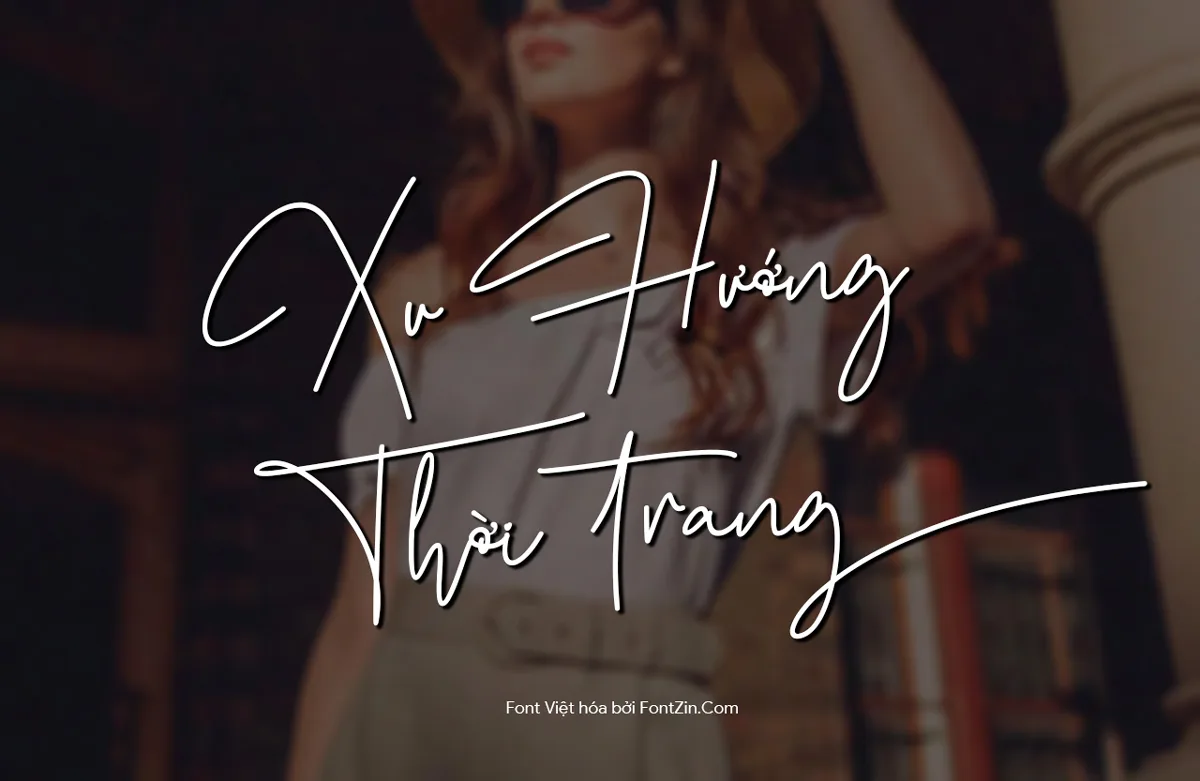
Tải Font Fz Fashion Signature Việt Hóa – Phông chữ ký thời trang, đẹp
Fz Fashion Signature là một font chữ ký viết tay mềm mại và quyến rũ, hứa hẹn mang đến sự lãng mạn, tinh tế và tươi mới cho dự án của bạn. Được sáng tạo bởi Thomas Aradea, font chữ này bao gồm các ký tự viết hoa, viết thường, số, dấu câu, ký hiệu, các đường nét swash và hỗ trợ đa ngôn ngữ, đặc biệt là tiếng Việt.
Những điểm nổi bật của Fz Fashion Signature:
• Phong cách thanh lịch: Với các đường nét mượt mà, tinh tế, font chữ này tạo nên vẻ ngoài thời trang và sang trọng.
• Hỗ trợ đa ngôn ngữ: Font chữ hỗ trợ nhiều ngôn ngữ, bao gồm cả tiếng Việt.
• Ứng dụng đa dạng: Phù hợp cho các dự án thời trang, thiết kế đồ họa, thương hiệu, watermark, typography, thiệp mừng, poster, danh thiếp, bài đăng mạng xã hội, tạp chí, bìa sách, thiệp mời, đám cưới, nhiếp ảnh, thời trang, quần áo, thư từ và văn phòng phẩm.